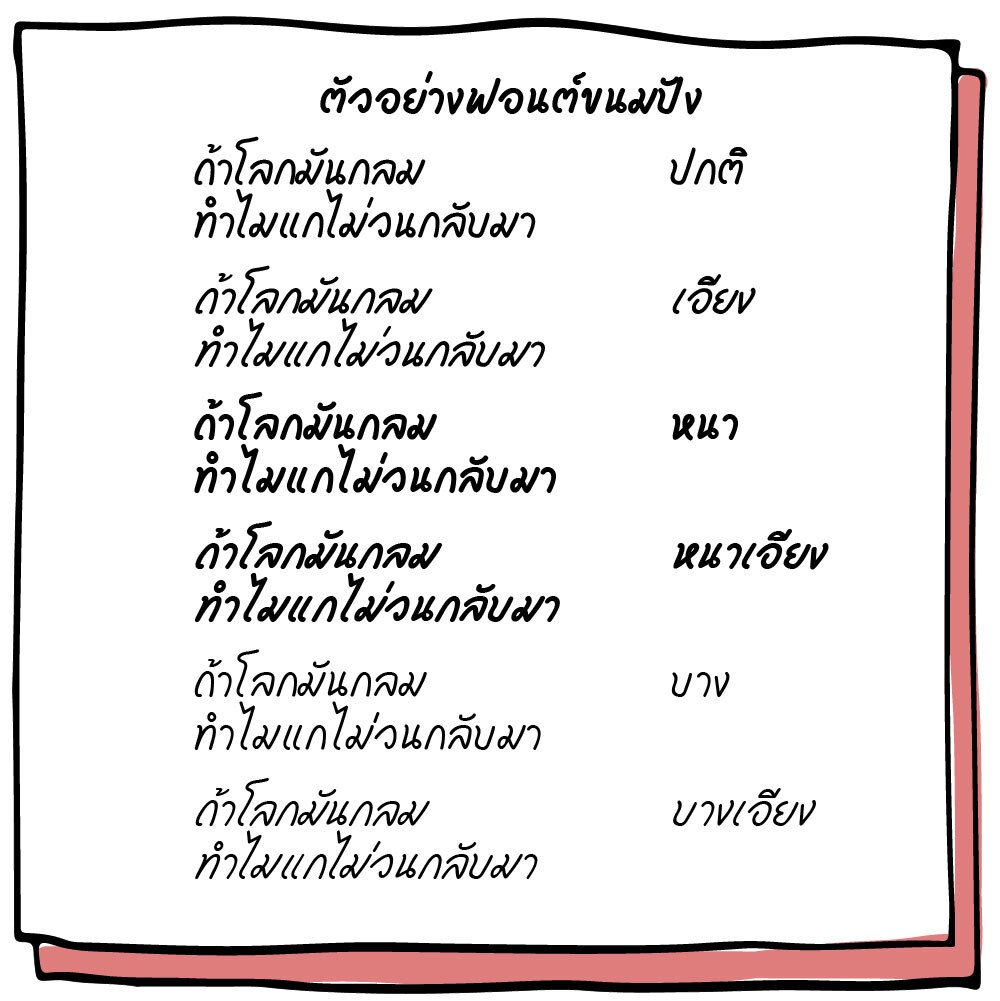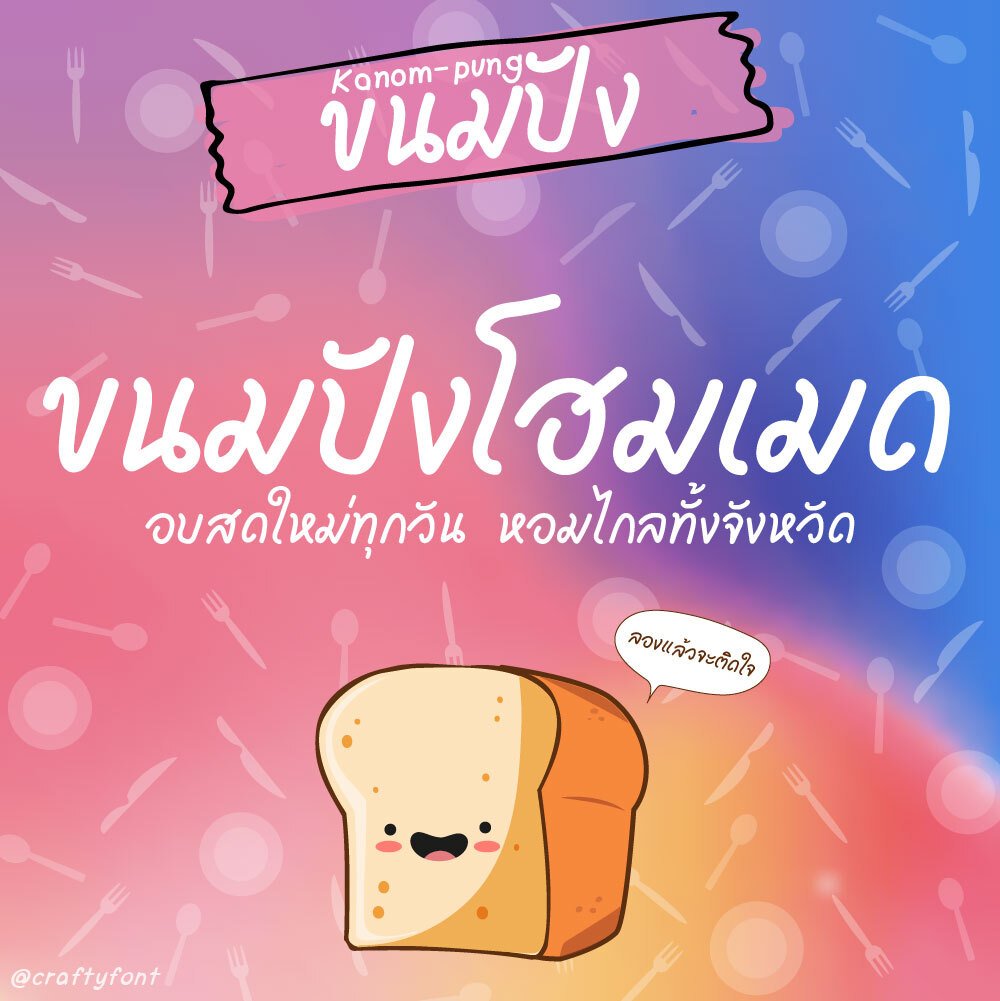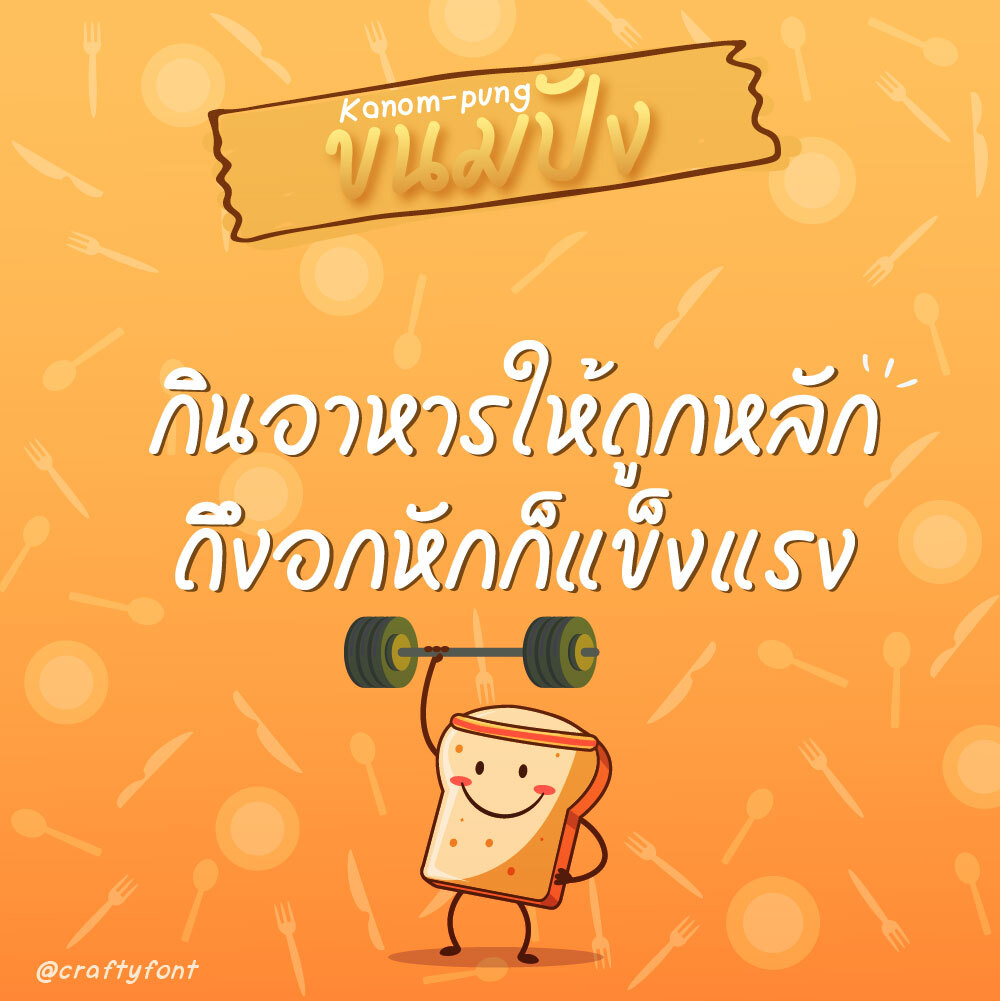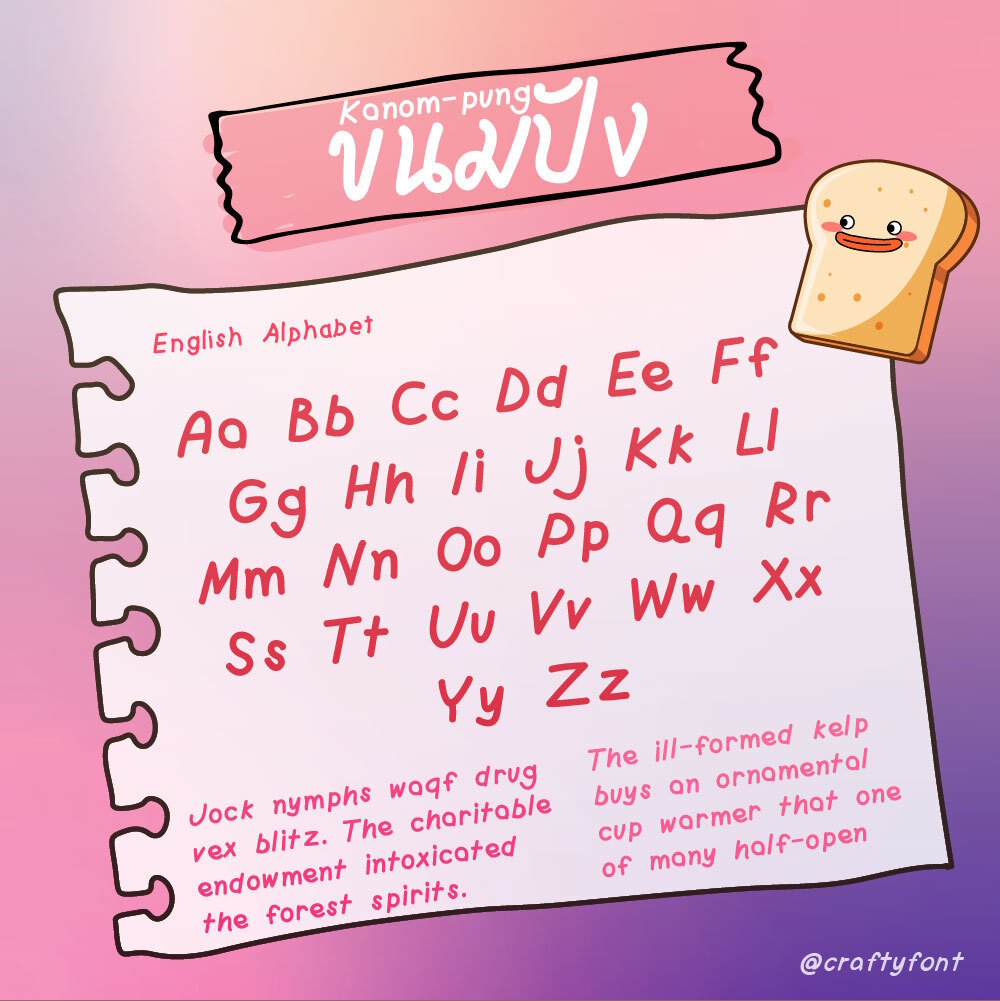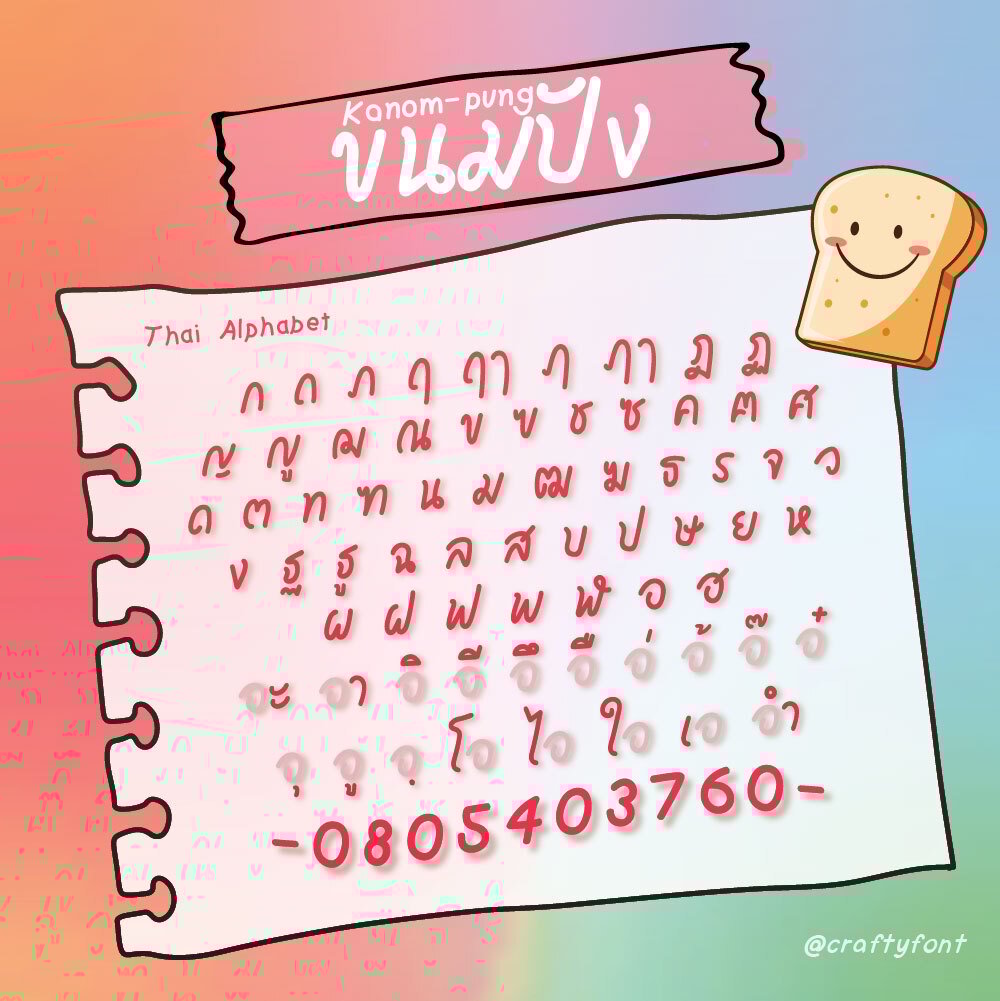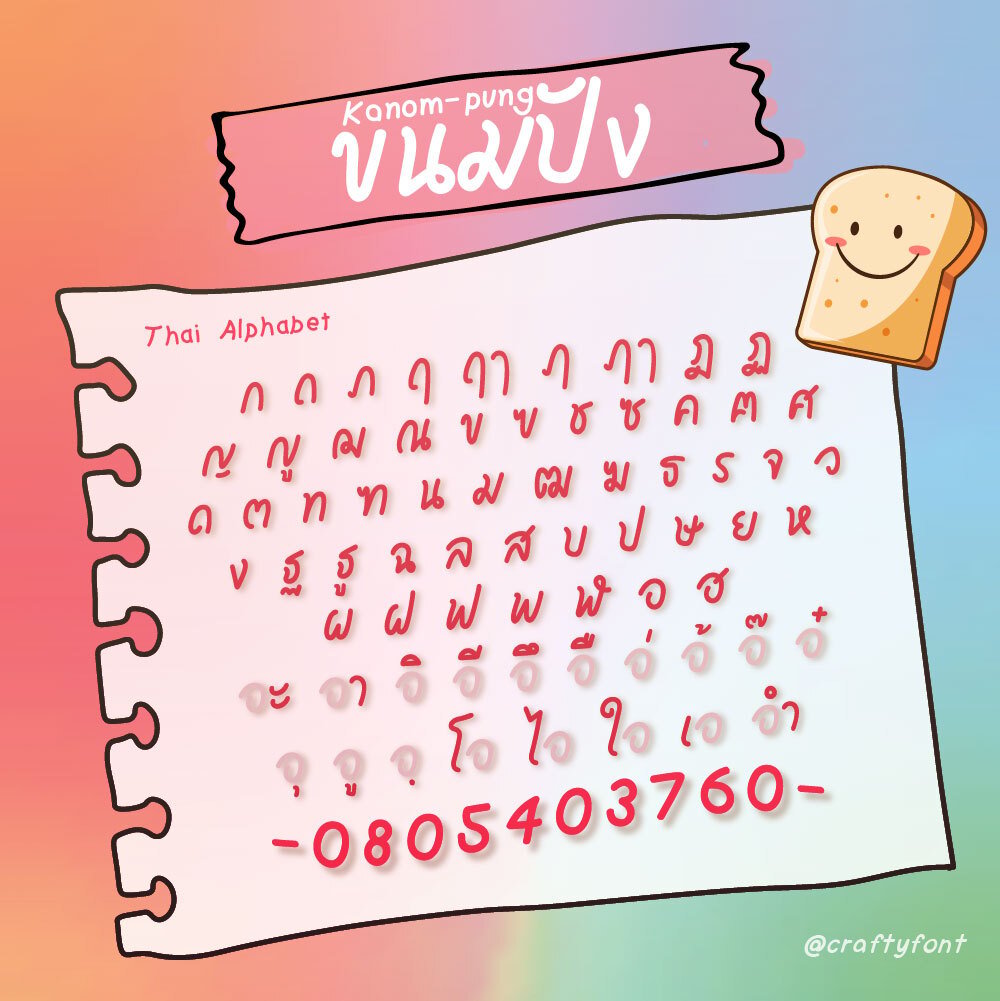
Kanom-pung Font (ฟอนต์ขนมปัง)
ฟอนต์ขนมปัง (Kanom-pung) ก้อนนี้เป็นขนมปังโฮมเมด เลือกใช้วัตถุดิบเกรดพรีเมี่ยม พิถีพิถันทุกกระบวนการ หวังว่าทุกคนจะชอบนะคะ 🍞🍞
ฟอนต์ขนมปังเป็นฟอนต์ไม่มีหัวตัวที่ 5 ของ Crafty font มีทั้งภาษาไทยและภาษาอังกฤษ แฟมิลี่เซ็ตนี้มี 6 ขนาดด้วยกัน ทั้งตัวหนา ตัวปกติ ตัวบาง และตัวเอนสำหรับทุกน้ำหนัก สัญลักษณ์บวกลบคูณหารมีให้ใช้ครบ ฝากไว้ในอ้อมอกอ้อมใจพี่จ๋าด้วยนะจ๊ะ